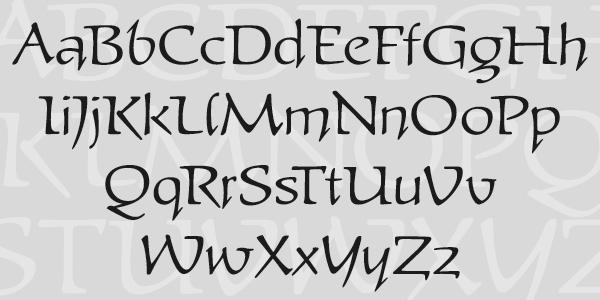
P22 veröffentlicht eine bislang unveröffentlichte Arbeit vom Chemnitzer Kalligraphen Heinz Schumann, der für seine Schrift Stentor bekannt ist, als digitale Schrift mit über 500 Glyphen: Schumann Pro. Diese Schrift war ein Projekt des Schülers von Albert Kapr und Herbert Thannhäuser während seiner Zeit an der Uni Leipzig.